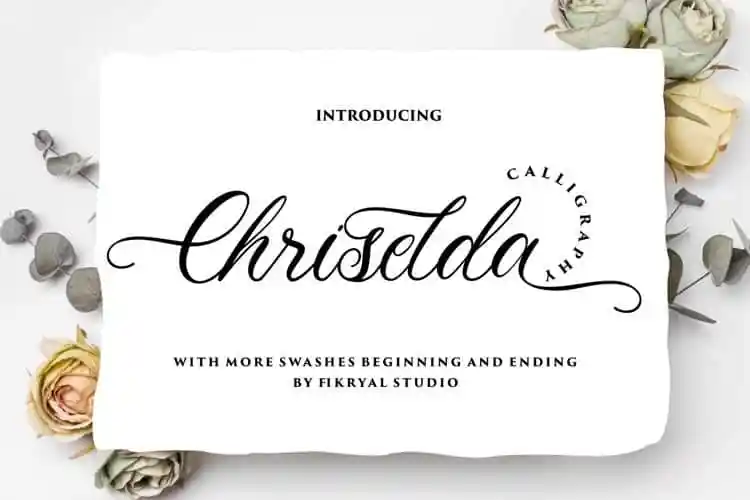
Chriselda Calligraphy Font – Download Grátis
Chriselda Calligraphy Font é uma nova qualidade do tipo tipográfico calligrafia que traz elementos contemporâneos e vintage dentro de seu design elegante. A fonte chama-se perfeito para qualquer projeto onde você quer dar um toque especial, como criação de materiais de bordão ou convites, embalagens de produtos, artefatos, postagem em redes sociais, anúncios, marcação em água e até mesmo eventos especiais. Com sua versão script moderna e vintage, Chriselda está pronta para tornar qualquer projeto mais atrativo e atraente. Este é um recurso visual que você pode usar para destacar seu trabalho ou produto com um toque único e sofisticado.